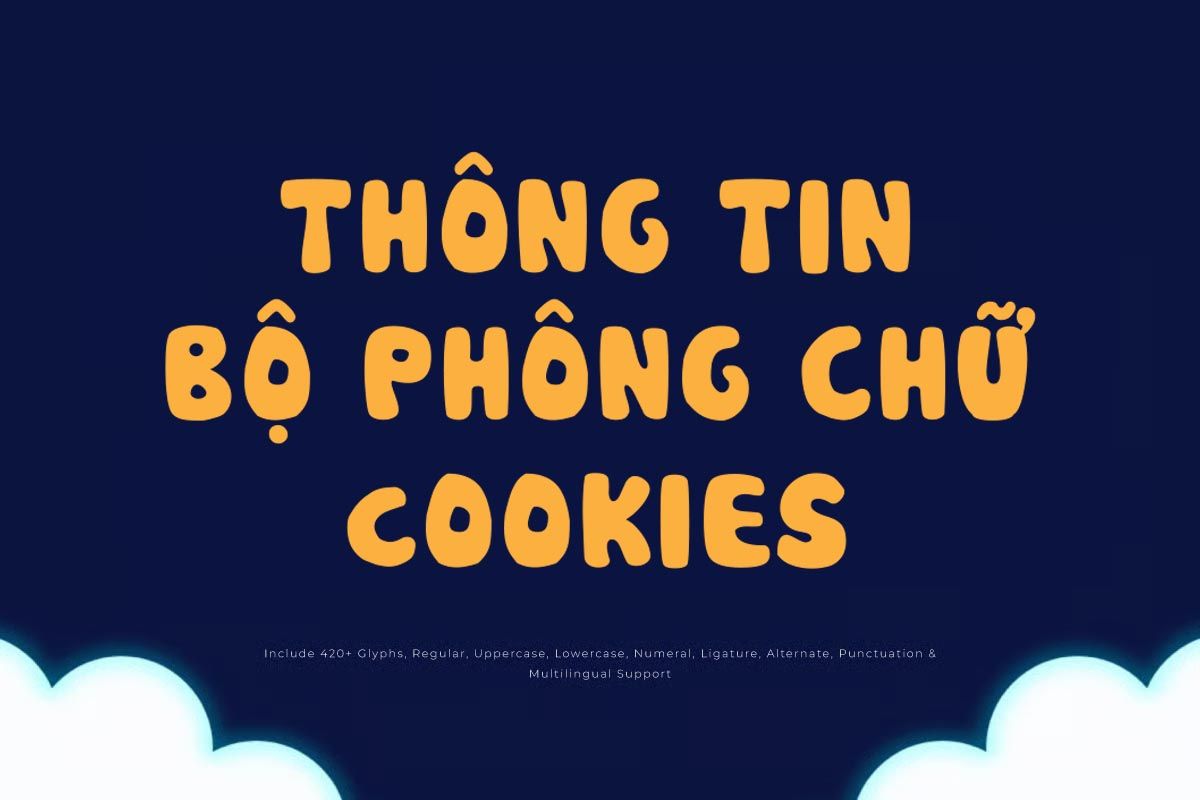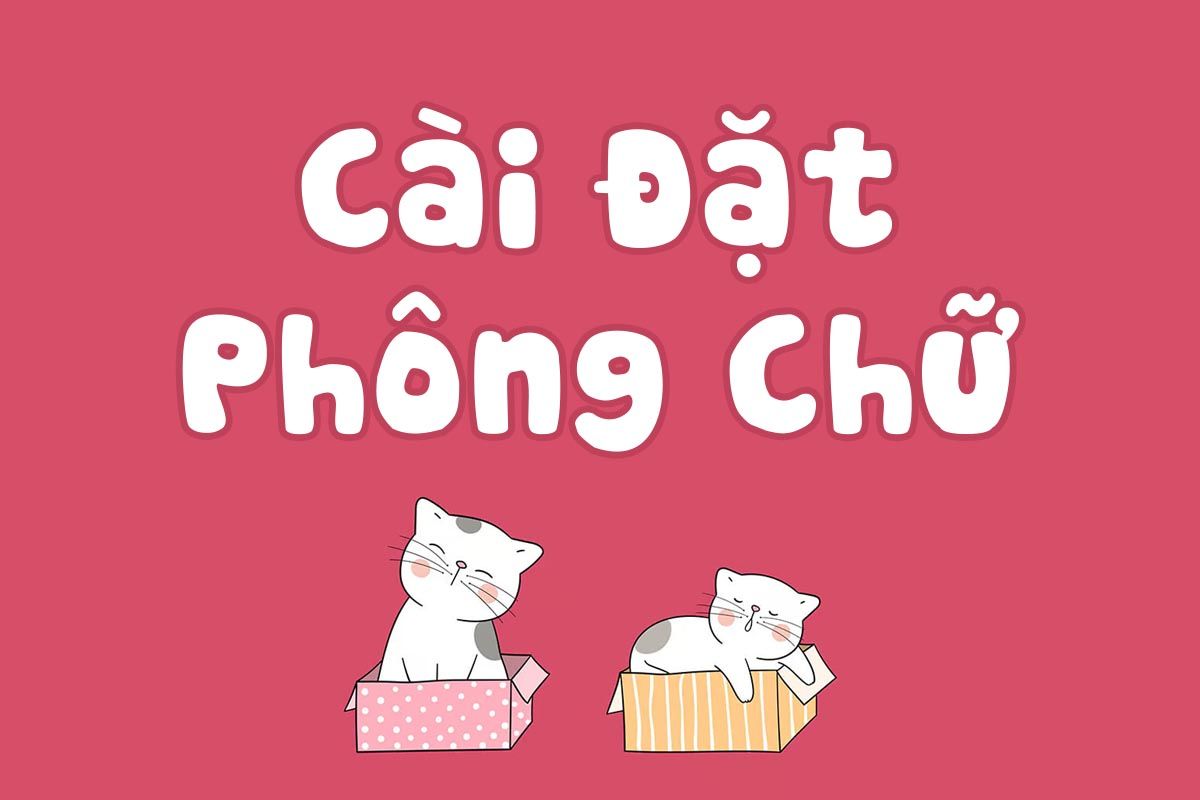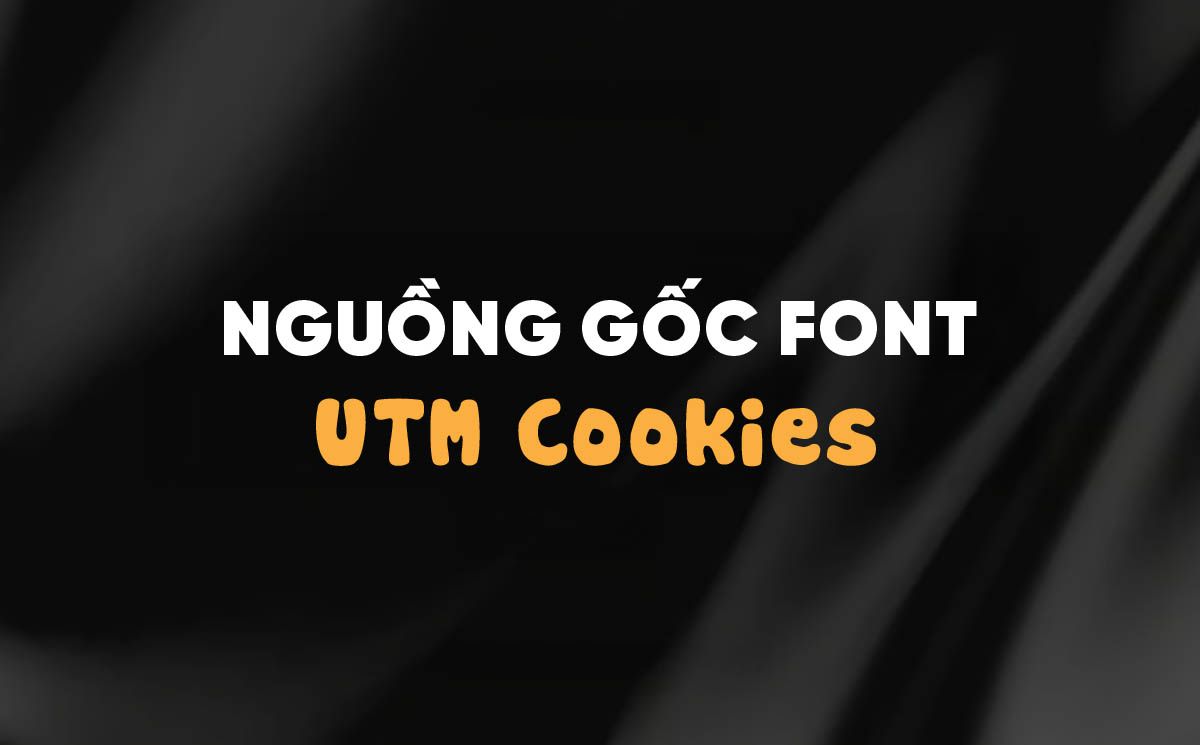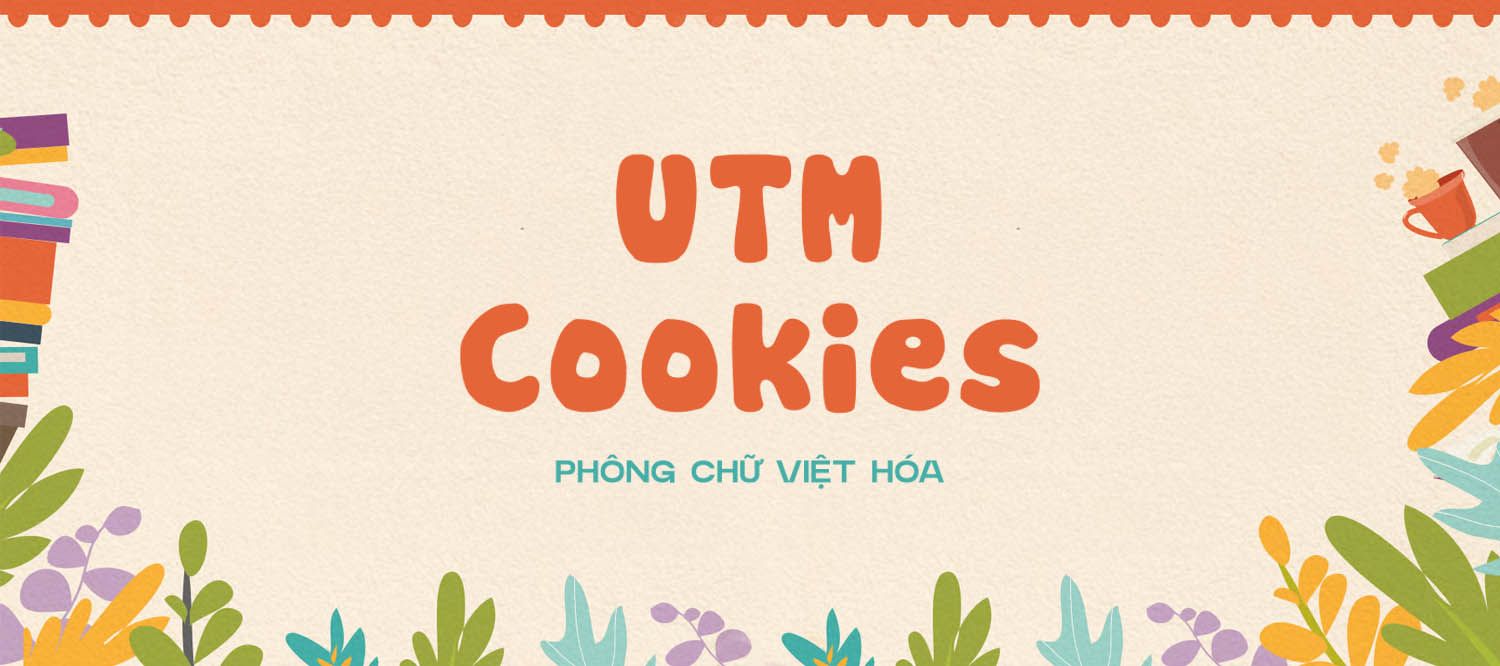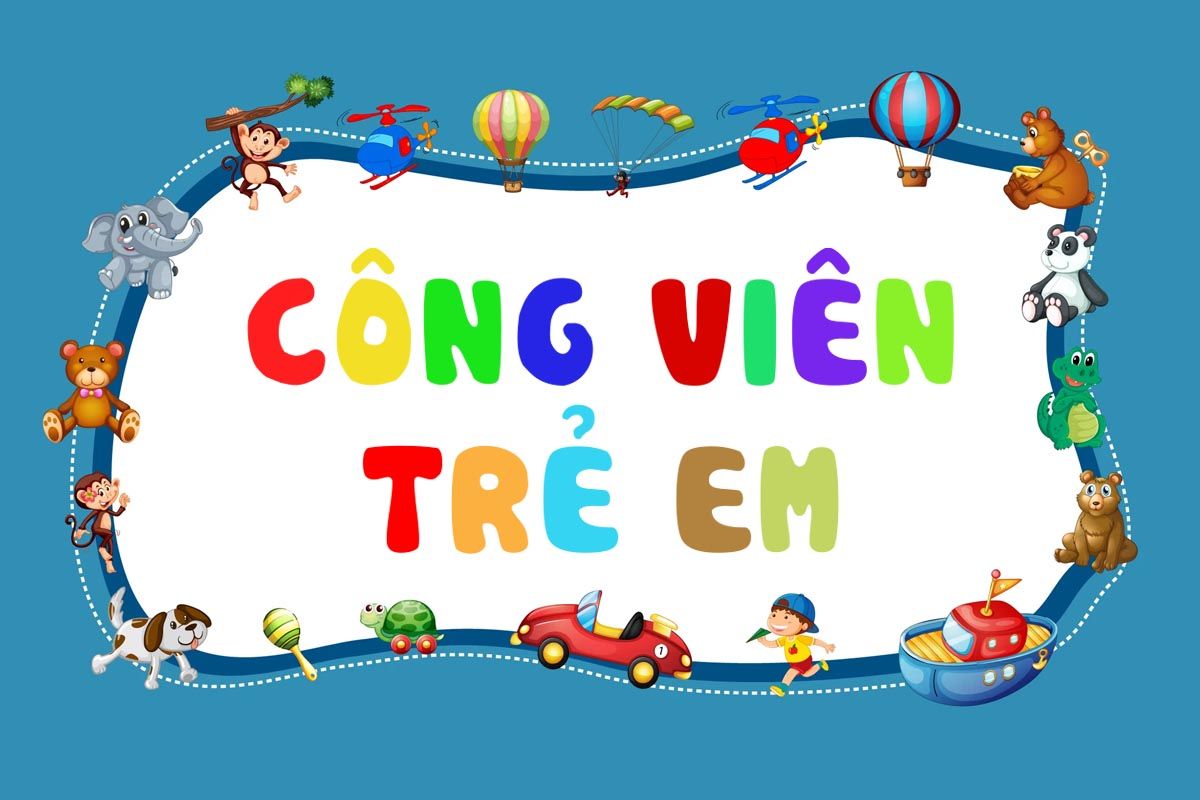
Font UTM Cookies là một font chữ viết tay Việt hóa, thuộc dòng display dễ thương và nổi bật. Kiểu chữ tròn trịa, dày dặn và mang lại cảm giác vui tươi, gần gũi – rất thích hợp cho các thiết kế hướng đến trẻ em, đồ ăn vặt, quán ăn, hoặc các sản phẩm mang tính giải trí.
Font UTM Cookies là phiên bản được Việt hóa bởi UTM – một đơn vị nổi bật trong cộng đồng Việt hóa font tại Việt Nam. Font gốc hiện chưa xác định rõ tác giả, nhưng được biết là được tạo ra bằng phần mềm Fontographer – công cụ phổ biến trong thiết kế font từ những năm 1990. Phiên bản gốc không hỗ trợ tiếng Việt và có giới hạn về bộ ký tự. Khi được Việt hóa, font đã được team UTM tinh chỉnh lại hoàn toàn theo hướng chữ tròn, đậm, mang phong cách display bubble vui nhộn – rất phù hợp cho các thiết kế bảng hiệu quán ăn, bao bì thực phẩm, hoặc ấn phẩm giáo dục dành cho trẻ em.
Font UTM Cookies mang phong cách display bubble với cấu trúc chữ tròn trịa, đều đặn và không có chân (sans-serif). Đường nét mềm mại nhưng mạnh mẽ, rất dễ đọc ở kích thước lớn – đặc biệt khi dùng trong tiêu đề, bảng hiệu hoặc các thiết kế cần gây chú ý thị giác nhanh. Đây là font chữ lý tưởng cho các thiết kế vui nhộn, đáng yêu và thân thiện.
UTM Cookies là một display font, cụ thể hơn thuộc nhóm bubble font – chữ dạng bong bóng, bo cong và phồng đều. Khác với handwritten hay script thông thường, font này không mô phỏng bút viết mà nhấn vào sự tròn đều, tạo cảm giác dễ thương và bắt mắt.
Nét chữ dày, bo góc tròn tạo cảm giác mềm mại nhưng chắc chắn. Font có xu hướng viết hoa đầu dòng, kết hợp chữ thường rõ ràng. Tỉ lệ ký tự hợp lý giúp font dễ nhìn cả ở dạng tiêu đề và body lớn – rất lý tưởng cho bao bì thực phẩm, tiêu đề poster, hoặc bảng thực đơn.
Unicode đầy đủ tiếng Việt: bao gồm các dấu như ă, ê, ô, ủ, ư...
Ưu điểm: Font UTM Cookies sở hữu nhiều ưu điểm nổi bật như: hỗ trợ đầy đủ tiếng Việt không lỗi dấu, kiểu dáng tròn đều dễ đọc và tạo cảm giác đáng yêu. Font có dung lượng nhẹ, dễ cài đặt trên mọi hệ điều hành, đồng thời rất phù hợp với các thiết kế dành cho trẻ em, ngành thực phẩm hoặc giáo dục. Nhờ đường nét đậm và mềm mại, font này còn tạo điểm nhấn thị giác hiệu quả khi sử dụng làm tiêu đề.
Giới hạn: Tuy nhiên, font hiện chỉ có một kiểu chữ duy nhất là Regular, chưa có phiên bản Bold hoặc Italic, và không thật sự phù hợp với các thiết kế mang tính trang trọng hoặc cần sự nghiêm túc cao.
Dù không có nhiều style như các font đa năng, UTM Cookies lại sở hữu cá tính thị giác rất riêng: vui tươi, ngộ nghĩnh và gần gũi. Đây là một font đáng có trong bộ sưu tập thiết kế dành cho trẻ em, giáo dục, thực phẩm, hoặc các thương hiệu mong muốn thể hiện tinh thần tích cực, dễ nhớ và đáng yêu.